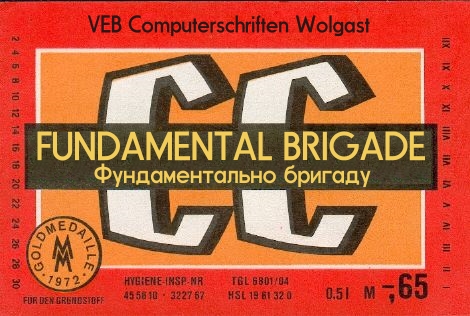
Welche Schrift ist das, mit Antwort TGL 0-1451 DIN1451
Wie die meisten von euch wissen, hatte die ehemalige DDR auch DIN Normen, die im Format TGL 0-1451 der DIN 1451 entspricht.
hier  sind ein paar Fundstücke
Bitte beachtet, dass viele TGL´s auf der ersten Seite einen Stempel tragen "Verbindlichkeit aufgehoben" danach folgt eine TGL Nr. mit welcher diese weitergeführt, ergänzt berichtigt usw. wurde.
Da ich leider nicht alle DIN Normen (Nummern) im Kopf habe müsstet ihr hier ergänzen.
Somit wird für Typodesigner, wie z.B. Peter Wiegel, der Grundstock gelegt, Schriften im historischen Kontext zu rekonstruieren.
Leider sind nicht alle TGL´s so gut gescannt oder erhalten, dass man eine saubere Schrift daraus erarbeiten kann.
Ein Beispiel aus der Peter Wiegel Schriftschmiede CatFont
ist die TGL 31034/01
Historisch interessierte Typodesigner werden da wohl eine Menge finden.
Dann gibt es auf diesem Server auch die Thematik Druck, Buchdruck usw. sowie die Thematik Farben.
Nur wenige RAL-Farben sind mit TGL-Farben indentisch.
TGL 12096 befasst sich mit der Gestaltung von Strassenverkehrsschildern usw.
Zunächst ein paar Worte zu den angeführten TGL-Standards: Diese tragen ja alle 3 eine TGL-Nummer die mit 0- beginnt. Dies sind zumeist sehr moderate Bearbeitungen der entsprechenden DIN-Norm (TGL 0-... ~ DIN ...). Welches DIN Blatt genau verwendet wurde, steht aks Hinweis im TGL Standard, es gab aber auch Fälle, wo einfach nur das westliche DIN-Blatt reproduziert wurde, und aus der Titelseite swr Rahmen des DIN-Blattes inerhalb des TGL-Rahmens abgebildet war.
In diesertv Zeit habe ich, wenn es an meinem eigentlichen Arbeitsplatz nicht zu tun gab auch in der FH-Bibliothek mit ausgeholfen, wenn in die dortige Normblatt-Auslegestelle die neuen Ausgaben einsortiert werden müssen. Und so hatten wir dort nicht nur die komplette Bibliothek der DIN-Normblätter, sondern auch ebenso alle TGL-Standards.
Und während die westdeutschen DIN-Normen vielfach an ANSI-Normen angepasst wurden, wenn sie nicht gänzlich durch ISO-Normen ersetzt werden erfolgte eben in der DDR eine Anpassuing an Russische GOST Standards, sodass sich dann der einstige TGL-0-Standard immer mehr vom entsprechenden DIN-Blatt entfernte, und so dieses Blatt dann eine eigene TGL-Nummer ohne 0- bekam. In der Normblatt-Auslegestelle haben wir, anders als bei den unter gleicher Nummer ersetzten Normblättern dann das alte Normblatt im Ordner belassen, Ungültig gestempelt und die neue TGL-Nummer auf das "Ersetzt durch" Feld eingetragen.